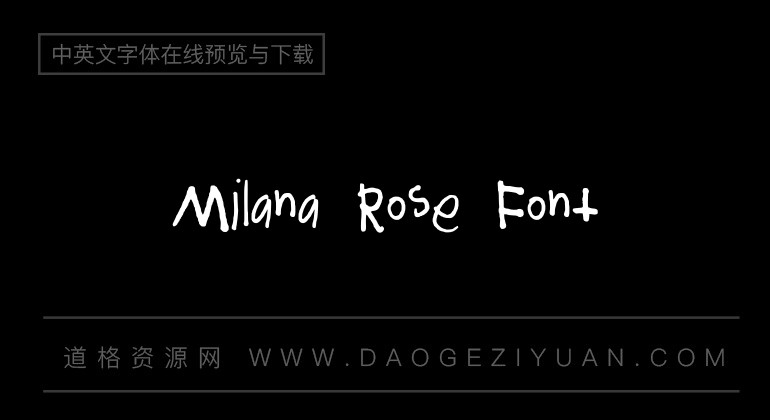
Milana Rose Font
Milana Rose是一种优美的手写风格字体,由著名设计师Maulana Creative于2019年设计。这种字体结合了传统的手写风格和现代的设计元素,给人一种温暖、亲切、自然的感觉。 这种字体的特点是线条流畅、圆润、柔和,字母之间的间距适中。它适用于多种设计领域,如印刷品设计、品牌设计、插图和装饰等。 Milana Rose字体家族包括Milana Rose Regular、Milana Rose Bold和Milana Rose Sans。每种字体都有自己独特的特点和用途,可以根据需要进行选择和搭配使用。 总的来说,Milana Rose是一种非常适合用于传达温馨、友好、亲切感觉的字体,它可以为设计作品带来独特的风格和感觉。
Milana Rose Font是一款非常不错的手写艺术字体,具有很好的视觉感,适合于文化类的宣传设计、商业类品牌的广告和产品包装设计以及个性化文字排版等较多场景。